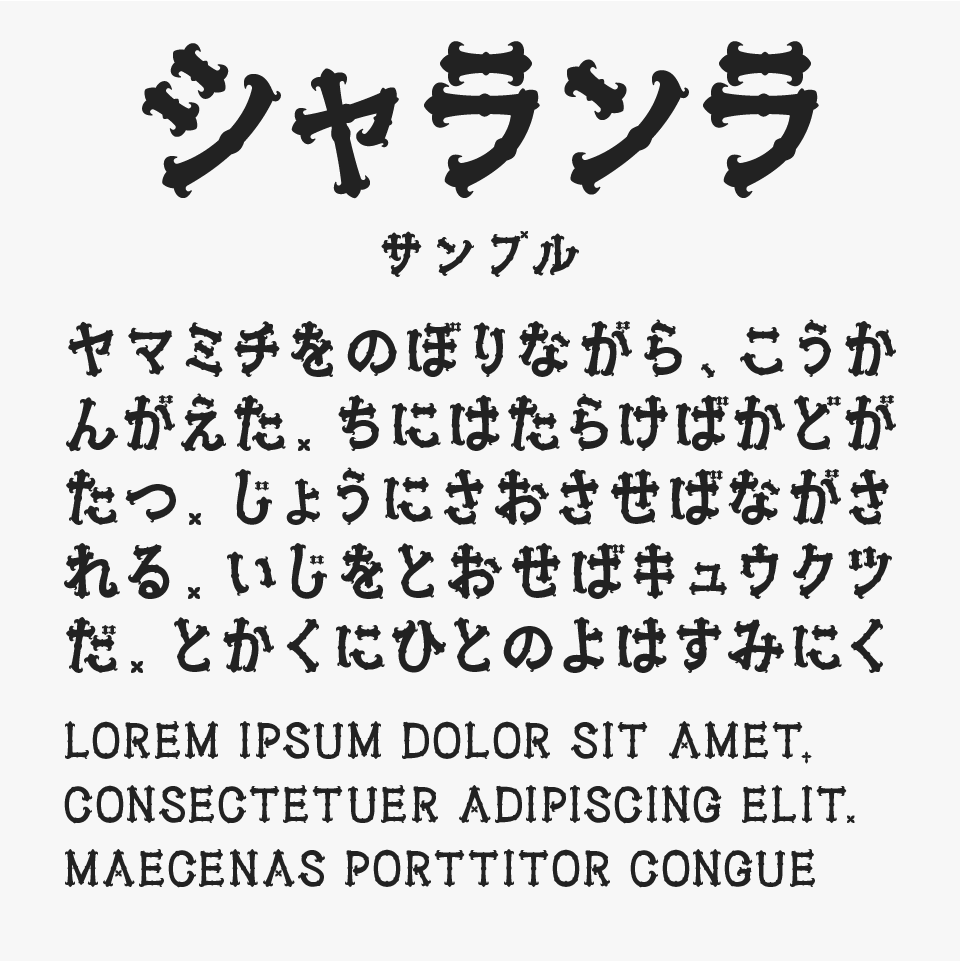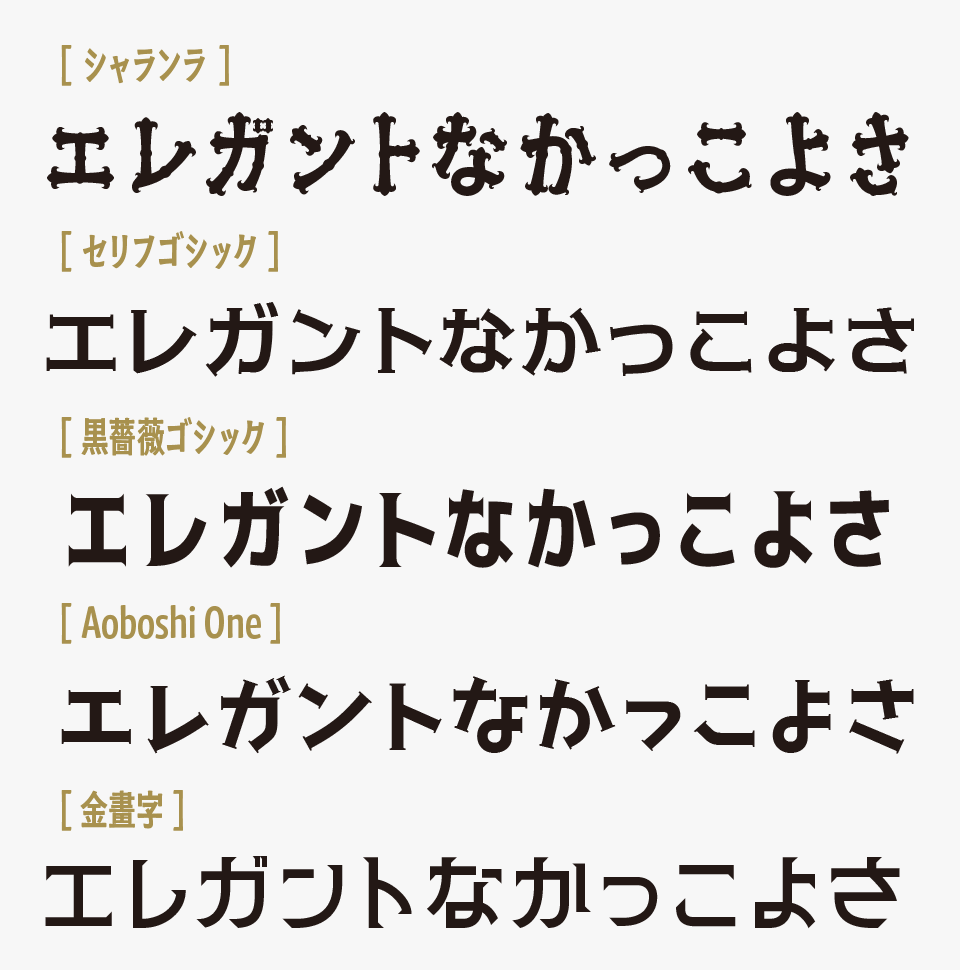
シャランラフォントは、文字の端々にアンティーク調の装飾的なふくらみや小さな突起をあしらいが入っているユニークなデザインフォントです。
少女漫画に登場する王子様やお姫様のような、高貴でゴージャスな雰囲気をまとったデザインです。華やかさと気品を兼ね備えたロマンチックで夢のある世界観を演出できる、印象的なフォントに仕上がっています。
少女漫画や乙女ゲーム、ファンタジー作品をはじめ、コスメやアクセサリーのロゴ、イベントビジュアル、パッケージデザインなどにぴったりなフォントです。気高さと華やかさを兼ね備えたシルエットが、作品にドラマチックな雰囲気を添え、まるで物語の主人公になったような特別感を演出してくれるフォントです。
シャランラフォントを、ほかのエレガントな雰囲気を持つフォントと比較してみると、華やかさの中にある可愛らしさと軽やかさが特に魅力のフォントです。
比較フォントは、「セリフゴシック」「黒薔薇ゴシック」「あおぼし(Aoboshi)」「金畫字(キンカクジ)」と使用していますが、どれも特徴的なエレガントなフォントなので、ぜひあわせてチェックしてみてください。